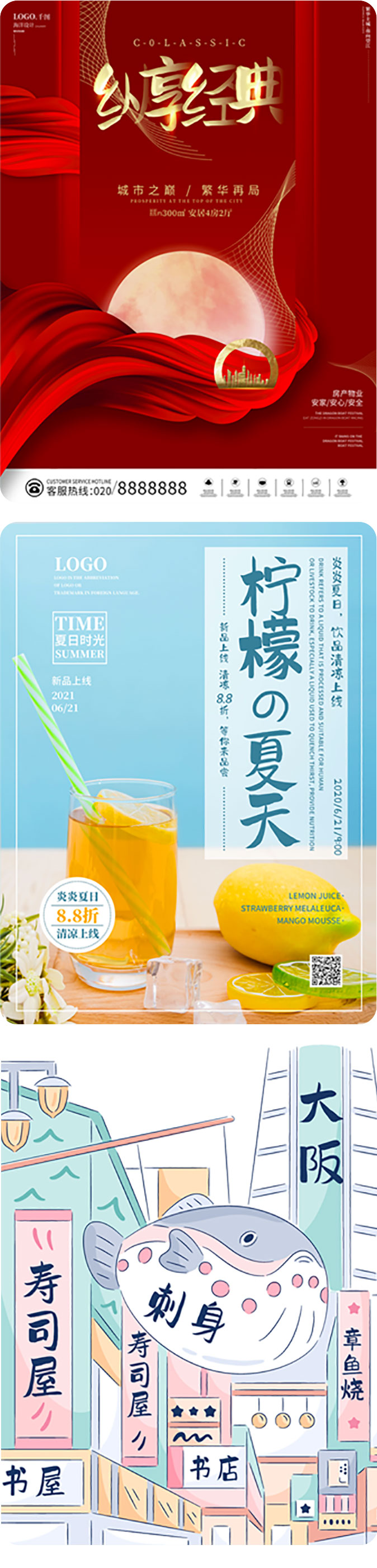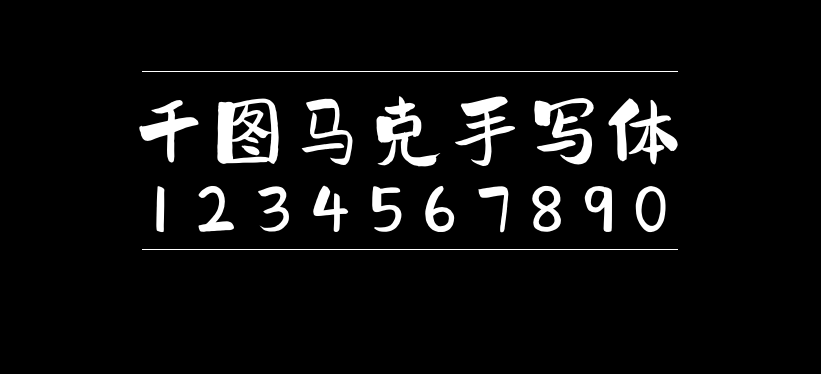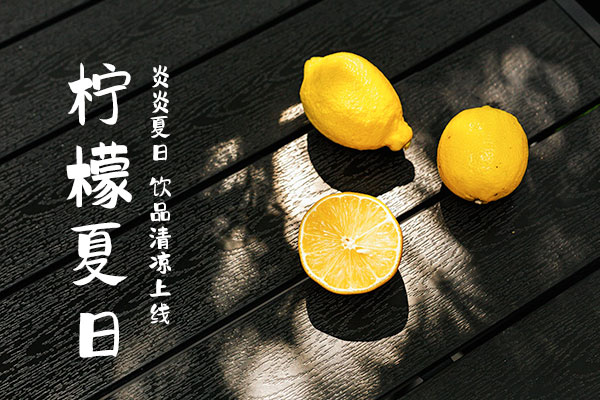
千图马克手写体
千图马克手写体是由千图网推出的一款免费商用字体,这是一款有着乐观感的字体。笔画开张有度,字面留有充足空间,字间保持合适的距离,让排列变得通透,阅读更加轻松、舒服,有如自在呼吸。既适合做标题又适合做提醒类的文字,适用于各类场景。
推荐场景:饮品/化妆品/日料/插画等,格式及字符:千图马克体包格式ttf,包含:西文52个、字母 464个、标点符号451个、数字118个、汉字9394个。
千图马克手写体是千图网联合国内专业字体设计机构字魂网共同发布的公益字体, 历时一年多悉心打磨完成。